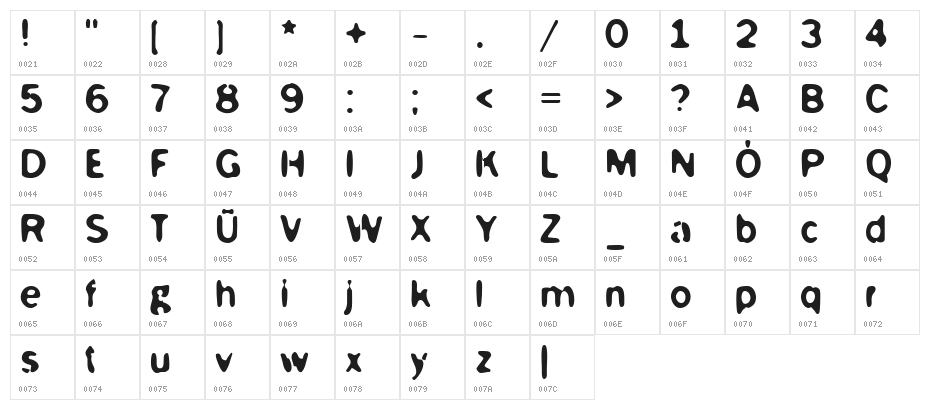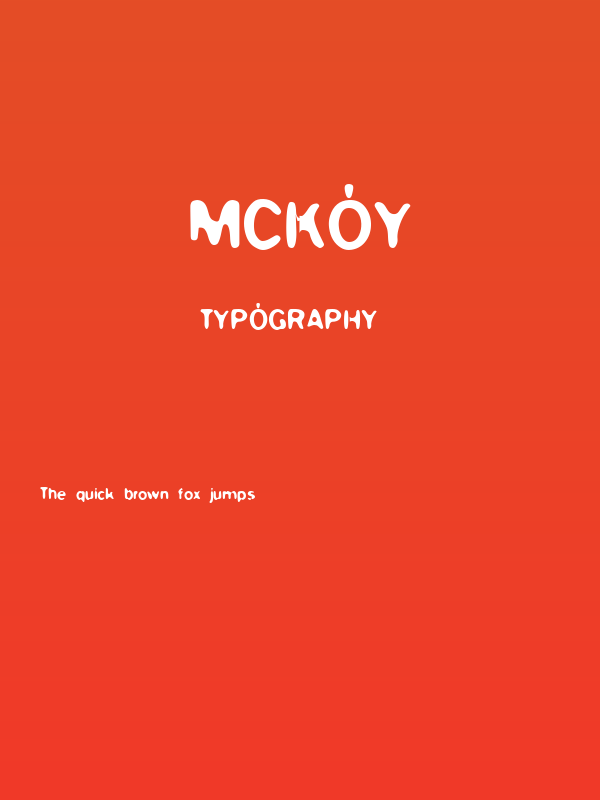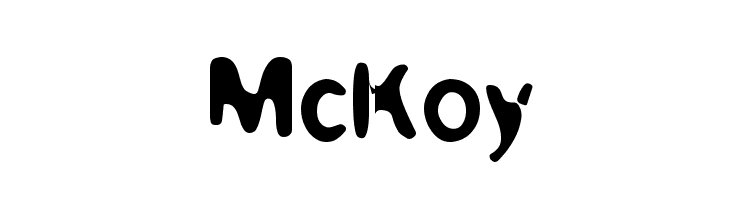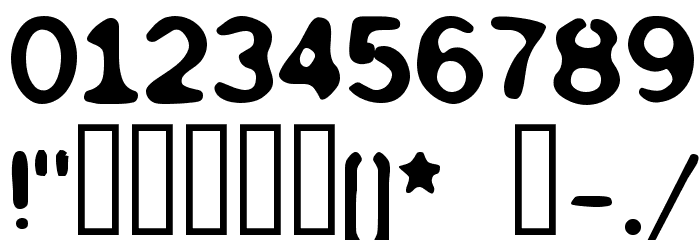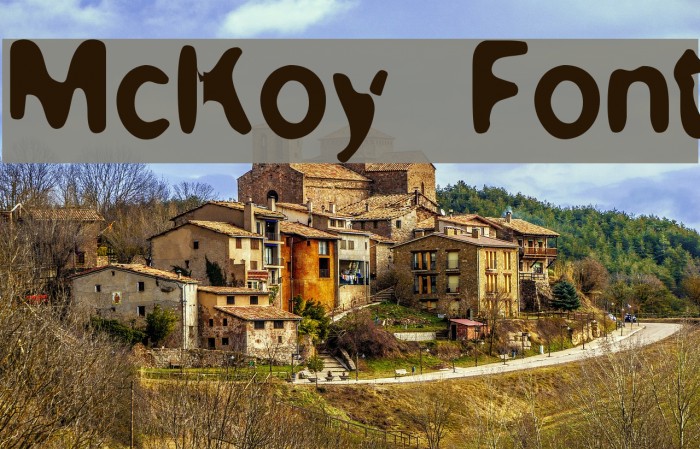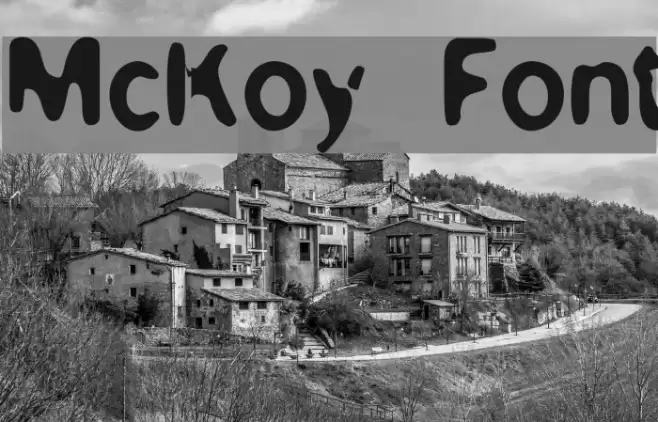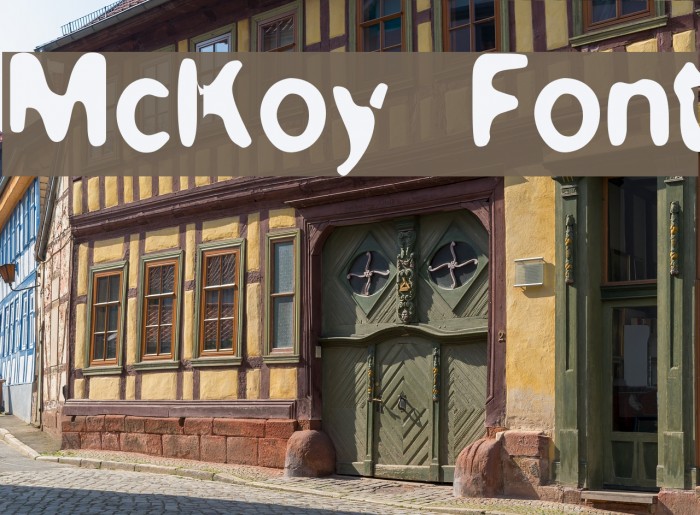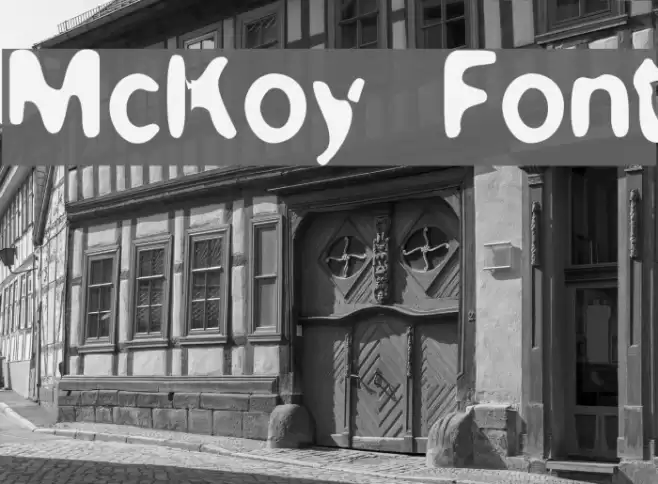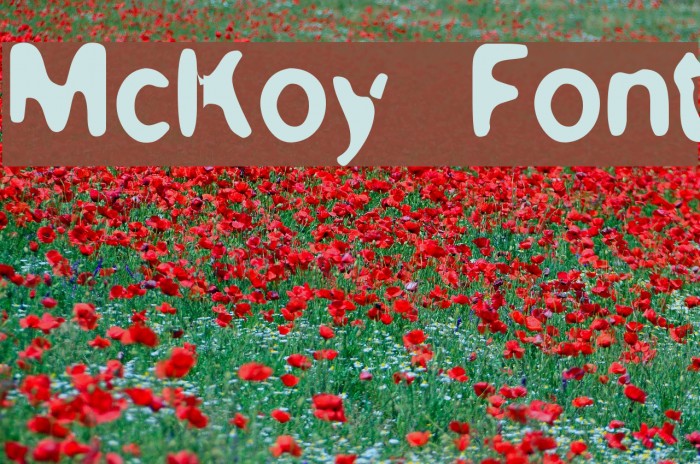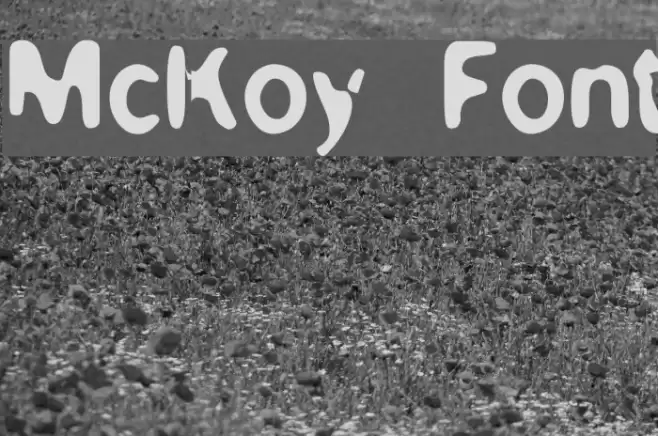
McKoy Font
✎ Distorted Eroded
| Categorii | Distorted Eroded |
| Stil general | Playful, Whimsical |
| Proiecte propuse | Ideal for children's books, playful branding, posters, and creative invitations. |